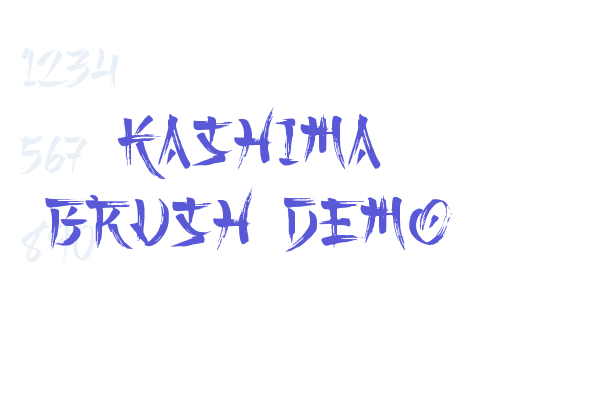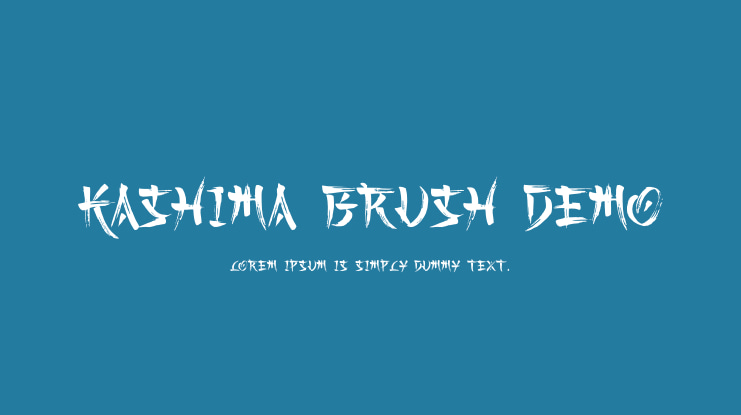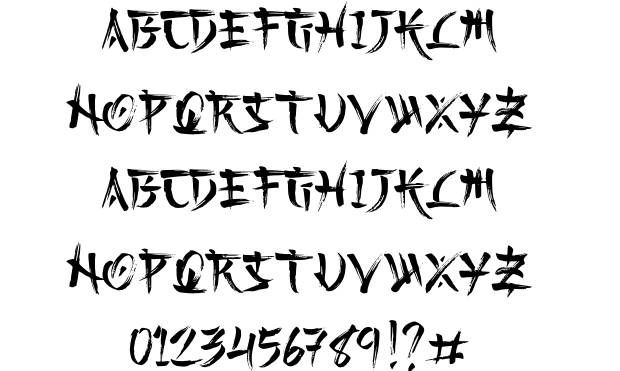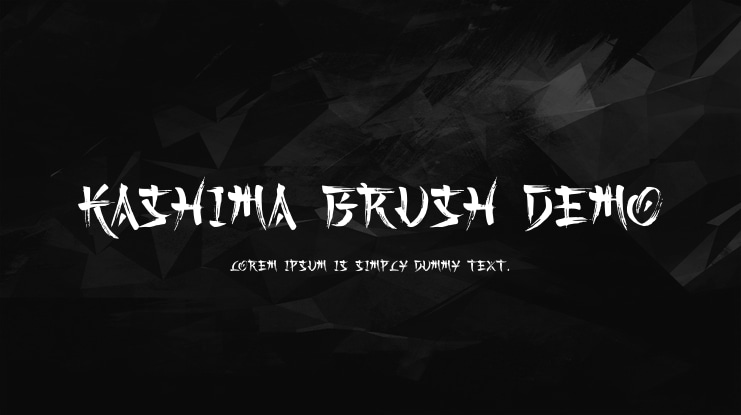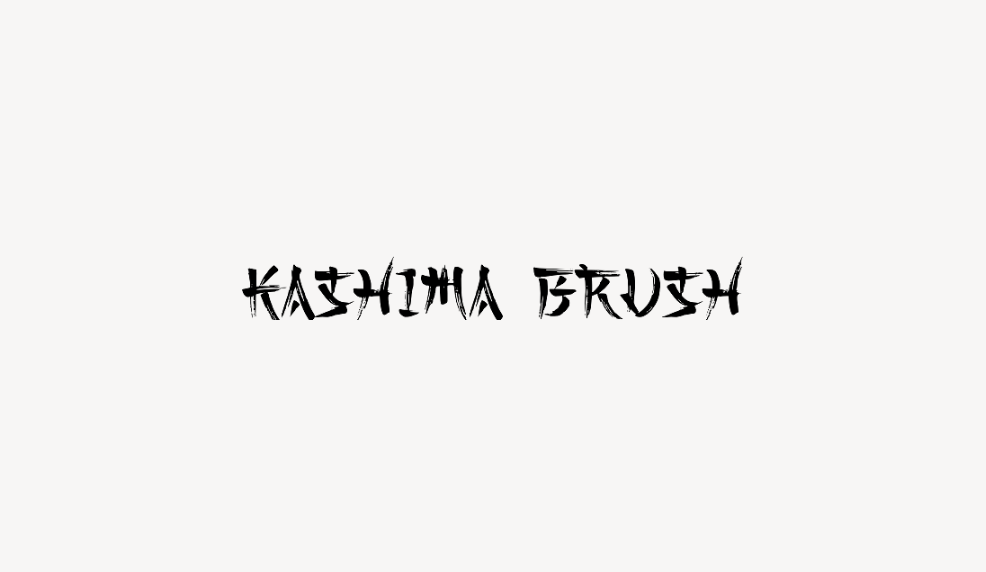
Đặc điểm thẩm mỹ độc đáo của bộ font SVN Kashima Brush
Kashima Brush không đi theo sự tròn trịa hay mềm mại của các phông chữ viết tay thông thường; nó tái hiện chân thực tinh thần võ sĩ đạo và sự uy nghi của nghệ thuật thư pháp cổ truyền.
Nét cọ thư pháp Nhật Bản (Shodo) đầy nội lực
Đặc trưng lớn nhất của Kashima Brush Font là cấu trúc nét vẽ mô phỏng lại những đường đưa bút lông bản lớn đẫm mực tàu trên giấy xuyến chỉ. Từng nhát nhấn, nhát hất và nhát vuốt đều toát lên sự mạnh mẽ, quyết đoán và chuyển động không ngừng. Cấu trúc chữ có độ dày nét lớn, tạo ra một sức nặng thị giác vượt trội, giúp tiêu đề bản thiết kế của bạn ngay lập tức chiếm trọn tâm điểm chú ý của người xem.
Hiệu ứng vệt mực ướt (Wet Ink) sống động và uy nghi
Các đường biên của SVN Kashima Brush giữ nguyên những gợn mực loang tự nhiên và những điểm cắt xẻ táo bạo, tạo cảm giác như một tác phẩm nghệ thuật vừa được đại sư thư pháp chấp bút trực tiếp. Phong cách này mang lại sự cổ kính, hoang dã nhưng vô cùng tinh tế, cực kỳ phù hợp với các dòng sản phẩm đặc sản, quà tặng lễ hội hoặc đồ uống thủ công.
Ưu điểm nổi bật của bản font SVN Kashima Brush Việt hóa
Khi ứng dụng các phông chữ thư pháp nước ngoài vào thị trường trong nước, sự chỉn chu về dấu câu là yếu tố quyết định đến tính chuyên nghiệp của bản thiết kế:
- Khắc phục triệt để lỗi dấu tiếng Việt: Phiên bản font SVN Kashima Brush Việt hóa đã được đội ngũ SVN trau chuốt thủ công từng dấu câu. Các dấu sắc, huyền, hỏi, ngã, nặng được vẽ đồng điệu với cấu trúc nét cọ đẫm mực, không tạo cảm giác chắp vá hay đè nét làm mất tính thẩm mỹ.
- Tương thích chuẩn bảng mã Unicode: Bản font cho phép bạn dễ dàng soạn thảo nội dung trên các bộ gõ tiếng Việt phổ biến như Unikey hay EVKey, hiển thị mượt mà trên mọi phần mềm đồ họa hiện đại.
- Bảo đảm tính đồng nhất thương hiệu: Việc tải font Việt hóa SVN Kashima Brush chuẩn giúp bạn tự tin dàn trang tiêu đề tiếng Việt mà không lo hiện tượng lỗi ô vuông hay nhảy về font hệ thống khô khan.
03 Ứng dụng thực tế của Kashima Brush Font trong sản xuất bao bì
- Hộp đựng Trà xanh & Bột Matcha: Nét cọ thư pháp Nhật Bản kết hợp cùng chất liệu giấy mỹ thuật nhám tạo nên vẻ đẹp nguyên bản, thanh tịnh và đậm đà phong vị trà đạo.
- Bao bì nhà hàng Nhật (Sushi, Ramen): Tiêu đề thương hiệu in bằng font Kashima trên túi giấy Kraft nâu mang lại cảm giác mộc mạc, truyền thống và chất lượng chuẩn mực.
- Nhãn dán chai rượu Sake & Đồ uống thủ công: Nét mực loang uy nghi của font chữ giúp chai lọ toát lên vẻ bí ẩn, mạnh mẽ và thu hút ánh nhìn trên kệ hàng.
03 Lưu ý kỹ thuật khi in ấn với phông chữ thư pháp nét cọ đậm